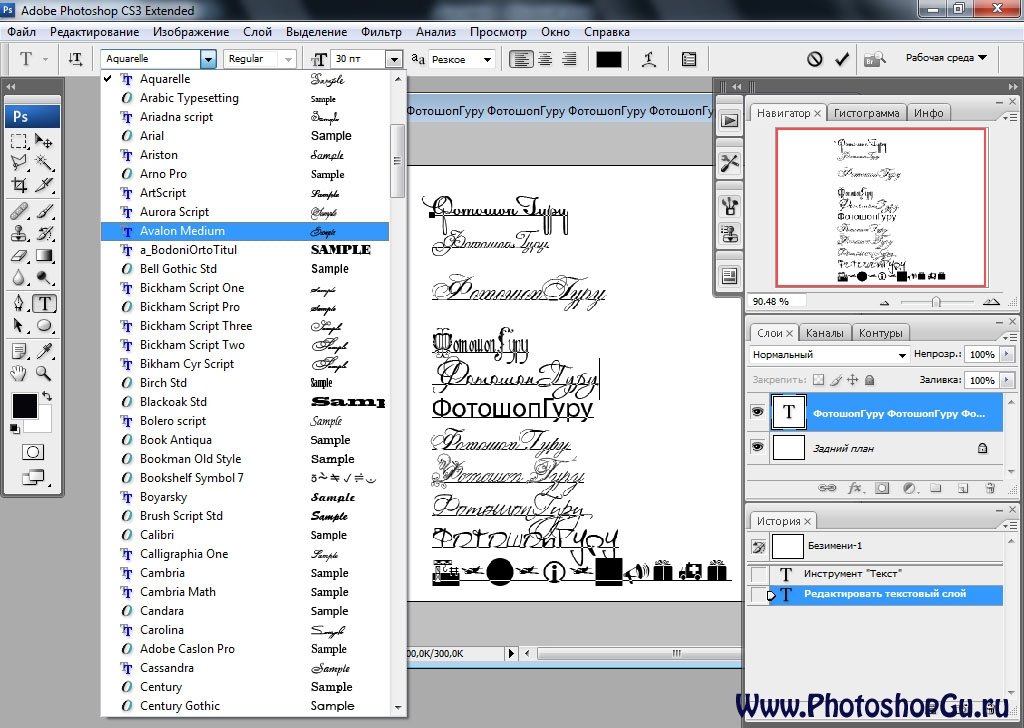
10 лучших шрифтов и гарнитур Photoshop для вашего следующего проекта
Как добавить шрифты в Photoshop? Как импортировать шрифты в Photoshop? и Список лучших шрифтов Photoshop. Что ж, беспокойтесь, не все вопросы о лучших бесплатных шрифтах для Photoshop рассмотрены в этой статье. Типографика — это нечто большее, чем просто подбор привлекательных шрифтов. Выбор любого шрифта, который вы хотите, и использование его в вашей работе не должны иметь место. Выбор правильного шрифта для вашего дизайна — самая сложная задача. Если вы не знаете, какой шрифт использовать, выбор лучших шрифтов для Photoshop может занять гораздо больше времени, чем создание дизайна. Шрифты должны быть не только эстетически привлекательными, но и соответствовать дизайну, должным образом передавать сообщение и быть удобочитаемыми.
Список лучших шрифтов PhotoshopСписок бесплатных шрифтов для Photoshop ниже:
Helvetica / Helvetica Neue / Helvetica Сейчас Helvetica — самый профессиональный и самый популярный шрифт.
Кто-то хвалит шрифт, а кто-то считает, что он расположен слишком близко друг к другу.
ФутураFutura — геометрический шрифт без засечек. Это один из крутых шрифтов Photoshop, основанный на геометрических фигурах, особенно кругах, похожих на стиль дизайна Баухаус. Он отличается чистыми и точными пропорциями.
ФосфатPhosphate поставляется со всеми буквами, геометрическими фигурами и уникальными глифами, которые делают этот шрифт наиболее ценным на рынке шрифтов. Он имеет жирные символы, которые хорошо подходят для названий и заголовков. Он легко привлекает внимание. Мы не рекомендуем его для обычного текста, потому что он дает смелое заявление.
Это традиционный шрифт с засечками, известный своей четкостью и разборчивостью. Когда вы пишете, это не занимает много места на вашей странице.
Хорошо смотрится в большем масштабе. Хотя он не так популярен, он хорошо подходит для основного текста и заголовка.
Вместо основных лучших шрифтов Photoshop. Если вам нужен курсивный шрифт. Вы можете использовать эдвардианский сценарий. Это эмоциональный, лиричный, страстный каллиграфический шрифт. На него повлияло письмо пером со стальным наконечником.
Этот шрифт отлично смотрится на приглашениях на вечеринки, свадебных приглашениях и благодарственных открытках. Мы не рекомендуем его для основного текста, потому что для этого он неразборчив.
АматикAmatic отличается стилизованным характером и отличной читабельностью. Этот шрифт для Photoshop — отличный выбор для заголовков и других фрагментов текста, которые должны выделяться на фоне основного текста. Его гуманистический налет сразу меняет мировоззрение композиции.
Отличный выбор для заголовков. Он может удобно рассказать историю без каких-либо усилий по добавлению других элементов.
Этот шрифт для Photoshop — примечательный шрифт, который может конфликтовать с другими мощными типами шрифтов в вашем дизайне. Имеет аккуратные чистые и ровные края. Он хорошо работает как в качестве текста заголовка, так и в виде краткого текста описания. Он добавляет уникальное чутье в атмосферу вашего дизайна.
Траян ПроЭто один из лучших шрифтов Photoshop. Trajan — шрифт с засечками в старом стиле. Это элегантный шрифт, который хорошо подходит для оформления книг, журналов, плакатов и рекламных щитов. Дизайн основан на римских квадратных капителях, основании колонны Траяна, от которой шрифт получил свое название.
Sabon — шрифт в древнем стиле. Один из крутых шрифтов Photoshop. Это любимый шрифт типографов и профессиональных дизайнеров. Из-за своей тонкой гладкой природы. Он идеально подходит для книжного текста или других элегантных дизайнов.
Бикхэм Скрипт Про Это формальный плавный шрифт, основанный на письме мастеров письма 18-го века.
Кэмерон Молл даже предложил это в своей статье, сказав: «Это один из шрифтов, за использование которого никто не будет уволен».
Целая коллекция причудливых шрифтов для Photoshop может сбить вас с толку в том, что лучше всего подходит для вашего дизайнерского проекта. Точно так же, как люди судят о вашей личности по тому, как вы выглядите и носите одежду, точно так же они оценивают ваш дизайн по тому, какой шрифт или элементы вы использовали.
22. Little Insect
Такой милый, Little Insect — еще один нарисованный от руки шрифт, идеально подходящий для детей или компаний с мягким, заботливым изображением.
23. Кепки животных
Каждая буква Кепки животных выглядит как старинный предмет. Хотя он не вписывается в современный графический дизайн, он настолько изобретателен; Я просто должен был включить его в этот список.
24. Sea Dreams
Sea Dreams выглядит так, как будто сам пострадал от береговой эрозии.